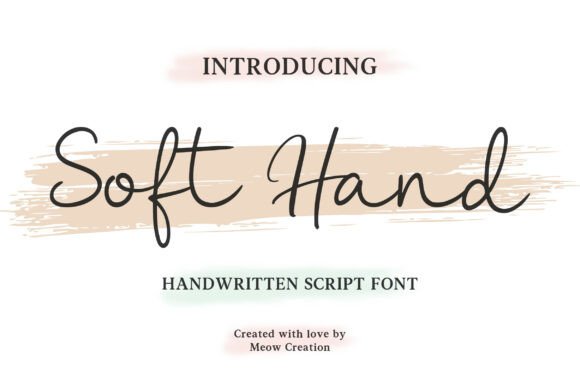
Soft Hand
Découvrez le Charme du Soft Hand : une écriture qui raconte une histoire
Dans un monde où la communication numérique prend le pas, le Soft Hand se démarque par sa beauté intemporelle. Créé par Meow Creation, ce type de police est plus qu’un simple tool d’écriture : c’est un geste pensé pour chaque lettre, conçu pour toucher le cœur de vos lecteurs.
Le Soft Hand se distingue par sa aérodynamisme fluide et une typographie élégante mais chaleureuse. Avec ses lignes soyeuses et ses boucles douces, ce script semble écrit à la main, comme si chaque mot était une promesse d’authenticité.
- Perfection pour les marques artisanales: que ce soit pour un boulangerie artisanale, un blog de bien-être ou une boutique de bijoux faits à la main, ce type de police apporte une touche de sophistication et d’intimité.
- Idéal pour les contenus profonds: que vous souhaitiez structurer des articles de design, des guides de mode ou des témoignages clients, le Soft Hand offre une lisibilité optimale tout en conservant son charme individuel.
- Un sourire dans chaque lettre: ce script est conçu pour inspirer confiance et bienveillance, idéal pour des invitations, des rapports de qualité ou des posts motivants.
Le Soft Hand ne se limite pas à l’esthétique : il incarne la sincérité d’une écriture personnalisée. En intégrant ce type de police à votre projet, vous créez une expérience visuelle qui parle directement à votre public, avec un style à la fois sophistiqué et humain.
Que vous soyez un créateur de contenu, un marketeur ou un artisan, le Soft Hand est le choix parfait pour imprimer de l’émotion dans chaque mot. Parce que chaque chose bien faite mérite d’être lue.